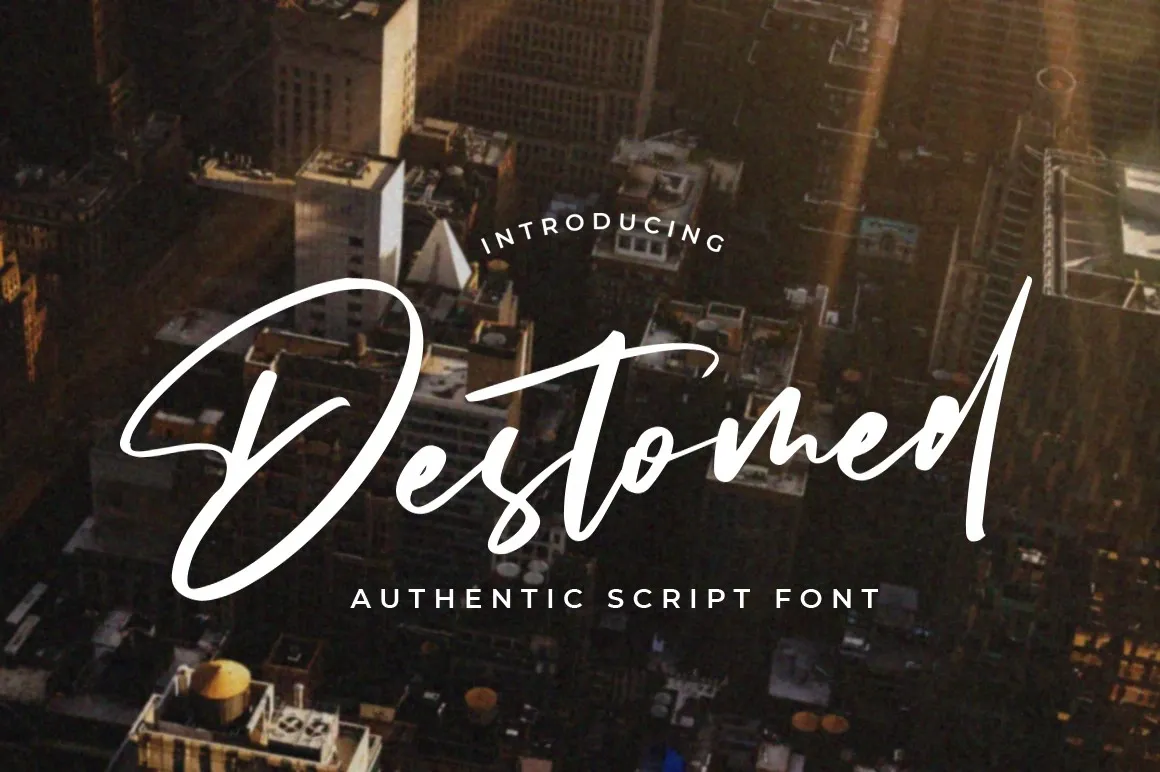
Essa fonte ‘Destomed Font’ é criada por Vultype Co., uma designer conhecida pela sua habilidade de criar tipografias cuidadosamente elaboradas. Esta script, com suas linhas leves e caracteres condensados, oferece um toque divertido com pequenas ligaturas. Ideal para quem procura uma fonte única e cheia de personalidade, é perfeita para projetos que buscam destacar-se e criar designs excepcionais. Não importa o projeto que você esteja trabalhando, a ‘Destomed Font’ tornará sua criação ainda mais especial e memorável.